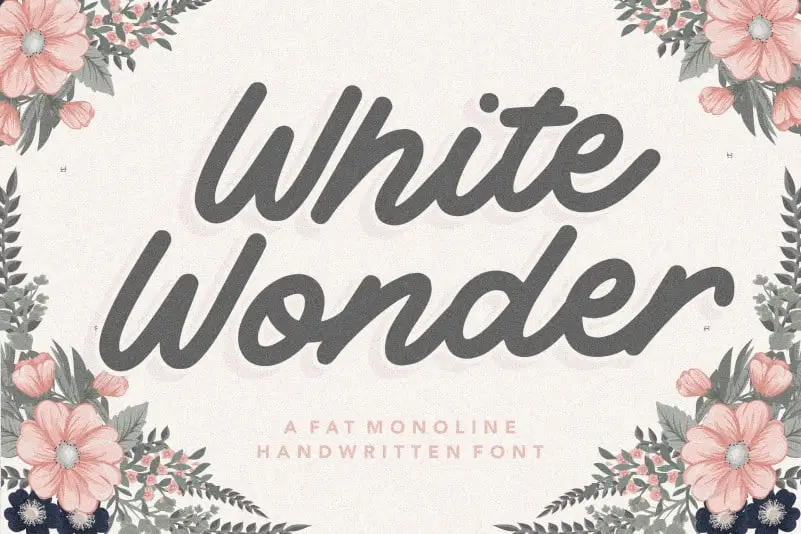
White Wonder Monoline Handwritten Font – Download Grátis
A ‘White Wonder Monoline Handwritten Font’ é uma fonte elegante e contemporânea ideal para diversas aplicações visuais. Suas linhas finas e sutis têm um toque natural que pode ser usado tanto no design de embalagens, como nas marcas de produtos, quanto na criação de magazines e redes sociais. Ela também é perfeita para expressar mensagens em pôsteres ou retratos criados sob fundo colorido, seja para uma campanha de wedding ou qualquer outro projeto que exija um tom casual e interessante. Esta fonte oferece uma opção limpa e moderna para aqueles que desejam dar destaque a suas mensagens sem perder o toque humano do estilo handwritten. Suas linhas monolineas proporcionam um aspecto sofisticado, ideal para estilos de design que valorizam minimalismo e elegância. Com ela, você pode expressar sua personalidade e criar designs únicos.